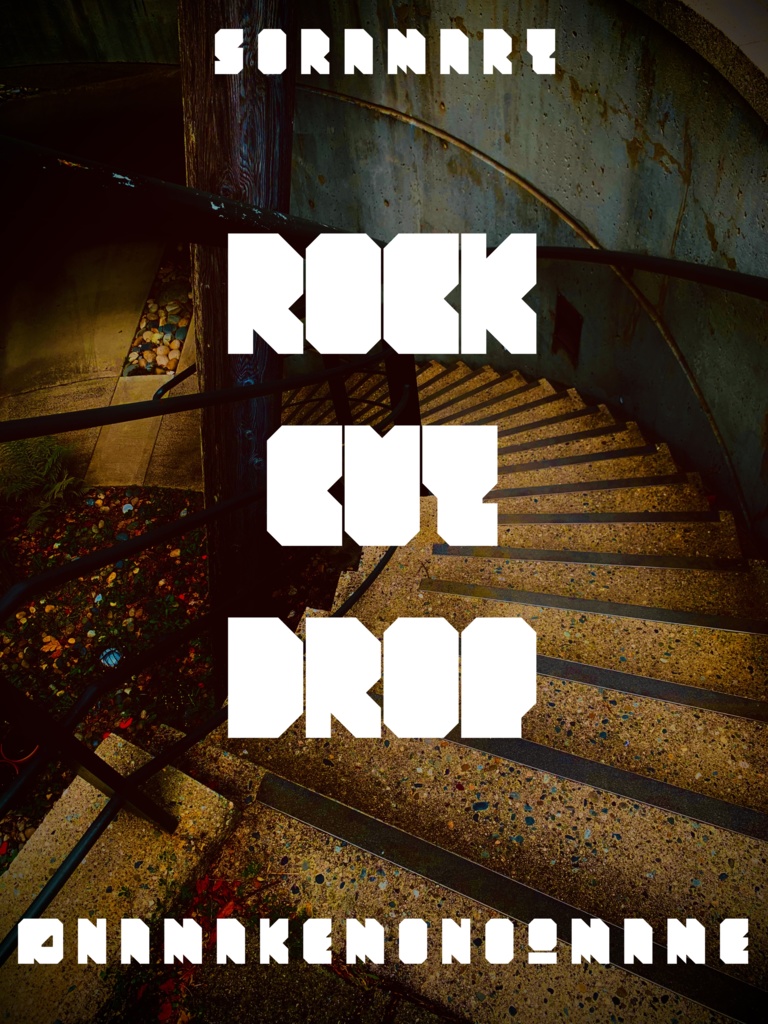
そらマートフォントデータ”Rock Cut Drop”Digital2,500 JPY加入购物车Buy a GiftAbout Giftブロックを無骨にカットしたようなシルエットのフォント "Rock Cut Drop" です。 「TrueTypeフォントファイル」という形式です。 ダウンロードした後、Zipファイル内のデータをインストールしてお使いください。 このフォントは商用利用可となっております。 お客様の制作・創作活動のお役に立てれば幸いです。 ※使用上の注意事項などは、添付のReadmeをお読みください。そらマートVisit FANBOX!Fontsフォントデータ”Eight-bit Quest Wide”そらマート0 JPYFontsフォントデータ”Eight-bit Quest”そらマート0 JPYFontsフォントデータ”Tonik Crate”そらマート0 JPYFontsフォントデータ”Vapor Sprout Edge”そらマート2,500 JPYFontsフォントデータ”Vapor Sprout Wide”そらマート2,500 JPYFontsフォントデータ”Vapor Sprout”そらマート2,500 JPYFontsフォントデータ”Star Shoot Ray”そらマート2,500 JPYFontsフォントデータ”Star Shoot Black Wide”そらマート2,500 JPYFontsフォントデータ”Star Shoot Black”そらマート2,500 JPYFontsフォントデータ”Mars Invader Balloon”そらマート2,500 JPYFontsフォントデータ”Mars Invader Wide”そらマート2,500 JPYFontsフォントデータ”Mars Invader”そらマート2,500 JPYFontsフォントデータ”Rock Cut Serif”そらマート2,500 JPYFontsフォントデータ”Rock Cut Drop Wide”そらマート2,500 JPYFontsフォントデータ”Longtail Sans Serif Slashed”そらマート2,500 JPYFontsフォントデータ”Longtail Sans Serif Bold”そらマート2,500 JPYFontsフォントデータ”Longtail Sans Serif”そらマート2,500 JPYFontsフォントデータ”Pretty Commando”そらマート2,500 JPYFontsフォントデータ”Abyss Dive Punk Retro”そらマート2,500 JPYFontsフォントデータ”Abyss Dive Punk Wide”そらマート2,500 JPY查看更多